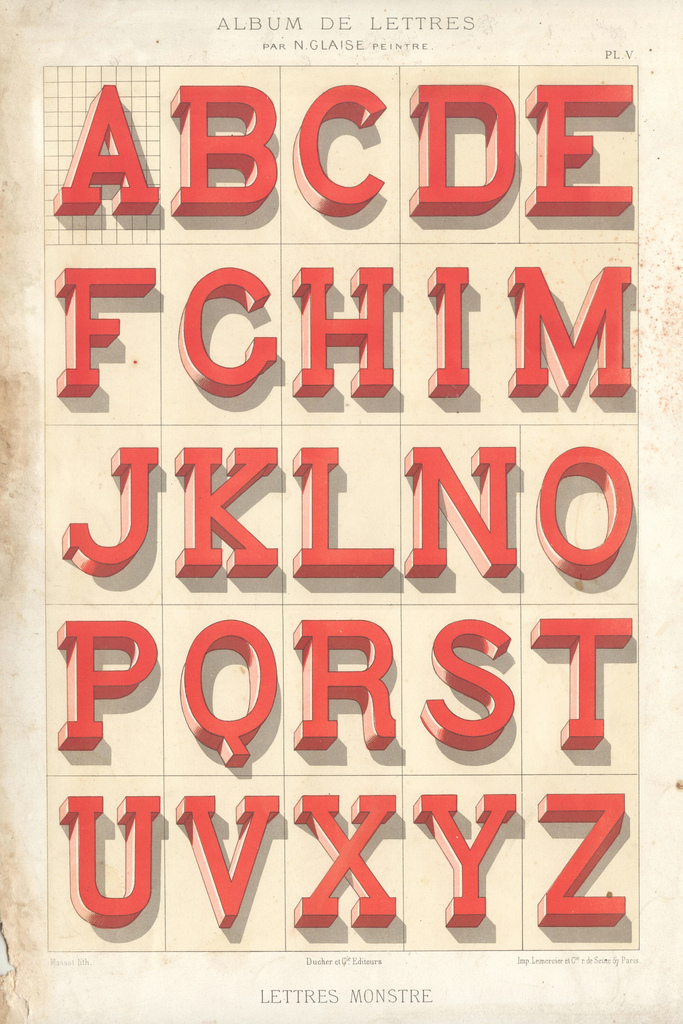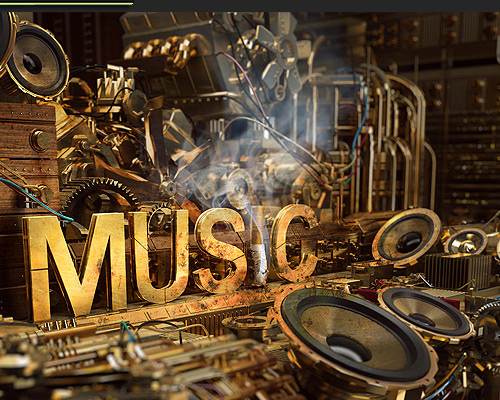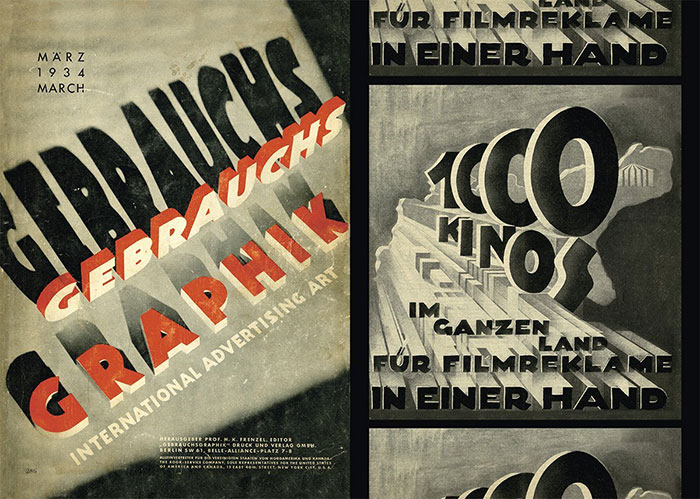
ich bin jetzt schon eine ganze weile auf der suche nach der "Geschichte" der 3D Typografie.
Ich würde gerne wissen ob es einen bestimmten Punkt gab wo das so "In" und modern geworden ist.
Also wie ist die 3D Typografie zustande bekommen?! Als auch Photoshop und Cinema ins Leben gerufen worden sind?
Habt ihr 3D Typografie schon mal in der Werbung gesehen, als neues Stilelement?
Hier nochmal eine kleine Inspiration. Das in etwa meine ich :)
3D-Typografie gibt es schon ewig.
Im 19. Jahrhundert …
Im 20. Jahrhundert
Und spätestens seit den 1990ern dann als digitales Rendering.
Es ist eines von vielen möglichen Gestaltungsmitteln und taucht regelmäßig auf. Ich wüsste aber nicht, dass es in letzter Zeit einen Punkt gegeben hätte, wo so etwas generell »in« wurde.
Spätestens ab der Verwendung der Keilschirft vor 5500 Jahren ist 3D in Verwendung.  ;-)
Meine ganz subjektive Wahrnehmung:
Dass 3D-Typo als Trend wieder in ist, fiel mir als erstes bewusst bei der MediaMarkt-Werbung auf. Seit dem sieht man dieses übertriebene 3D überall. Zwischendurch und vorher hat’s das sicherlich auch gegeben, m. E. aber nicht so viel und auf die Spitze getrieben.
Aber wie gesagt es ist nur das was mir aufgefallen ist ...
Abgesehen von den gemeißelten römischen Versalien gab es glaube ich schon eine Zeit worin dreidimensionale Beschriftung richtig ‘in’ wurde. In meine Flickr-Galerie 3D Hinterglasbeschriftung habe ich zufälligerweise in den letzten Wochen Bilder von Beschriftungen mit diese Art von dreidimensionale Buchstaben gesammelt. Selbst habe ich solche Buchstaben in Davos fotografiert. Es handelt sich hierbei um die Beschriftung des berühmten Café Schneider. Die meisten teilen der Fensterbeschriftung sind ebenfalls mit dreidimensionalen Buchstaben gemacht worden. Ich kann dir nicht genau sagen wie alt das alles wirklich ist, aber es gab so um 1900 herum Firmen die solche Buchstaben produzierten. Habe davon mal Seiten aus einen Katalog fotografiert. Also alles bevor die Leuchtkästen und die Neon-Buchstaben ‘in’ wurden.
Die für die Hinterglastechnik verwendete dreidimensionalen Einzelbuchstaben wurden in der Regel vergoldet. Entweder nur Glanzvergoldung oder die Kombination von Matt- und Glanzvergoldung. Sie wurden anschließend auf der Rückseite einer Glasscheibe montiert. Die Glasscheibe wurde meistens auf der Rückseite schwarz angestrichen. Damit ist es eine dreidimensionale Variante der sogenannte Hinterglastechnik. Die war glaube ich weiter verbreitet. Hier noch eine weitere Galerie mit Beispiele der Hinterglastechnik. Ältere Werbetechniker könnten dir darüber eventuell noch etwas erzählen. Das Buchstabenmuseum in Berlin hat übrigens einen Satz von solche dreidimensionale Buchstaben in ihre Sammlung. Am besten da mal nachfragen! Dieses Bild mit einer Ladenbeschriftung in Dublin ist besonders interessant wie ich finde. Es zeigt auf dem ersten Blick vergoldete Buchstaben in Hinterglastechnik. Dadurch, dass die schwarze Farbe des Fensters sich gelöst hat, kann man sehen, dass dahinter immer noch die älteren dreidimensionalen Buchstaben einer älteren Beschriftung rumliegen …
Was Neon-Beschriftung angeht, kann ich dir beispielsweise das Buch ‘Berlin im Licht’ empfehlen. Alles schwarz-weiß fotografierte Neon-Beschriftungen im Berlin der der 1930er. Die vorhin erwähnte beschriftete Leuchtkästen sind an sich nicht dreidimensional. Man kann sie aber zu dreidimensionale, konstruktivistisch anmutende Leuchtkörper zusammenbauen. Der Jenaer Typograf Walter Dexel war in den 1920er einen der Vorreiter auf dem Gebiet. Weiterhin auch Max Burkhardt und einige anderen. Die meisten Kunsthistoriker sehen Walter Dexel gerne nur als Maler, seine konstruktivistische Werbeanlagen werden von denen als ‘Brotkunst’ angesehen. Das Buch ‘Dexel in Jena’ zeigt sehr überzeugend, dass diese Sichtweise eine objektive Betrachtung von den Arbeiten von Walter Dexel im Wege steht. Egal ob Kunst oder angewandte Kunst, bei Dexel stammen beide aus der gleichen Vision.
Außerdem zeigen die Bücher von Nicolete Gray, dass im 19. Jahrhundert die dreidimensionale Schriften sehr angesagt waren. Und nicht nur in Groß-Britannien und die USA. Dieses Schriftmuster von der Schriftgießerei Laurent et Deberny (später wurde daraus Deberny Peignot) aus Paris (1837) zeigt, dass auch in Frankreich solche Schriften sehr beliebt waren. Wenn mir nichts alles täuscht, weist vieles darauf hin, dass es solche Schriften sogar zuerst in Frankreich gab und dass diese erst später in andere Länder wie GB und USA auftauchten.
Gerade bin ich auf ein Beispiel "in freier Wildbahn" gestoßen. Das Titelblatt eines Klaviertrios von Louis Spohr, ca. 1850.
Der Scan ist leider nicht sehr gut, die 3D-Buchstaben aber gut zu erkennen. (Wie bei Notenausgaben dieser Zeit üblich, hat sich der Verlag bei der Auswahl der Schriften auch nicht lumpen lassen; Schriftmischung war das Gebot der Stunde.)